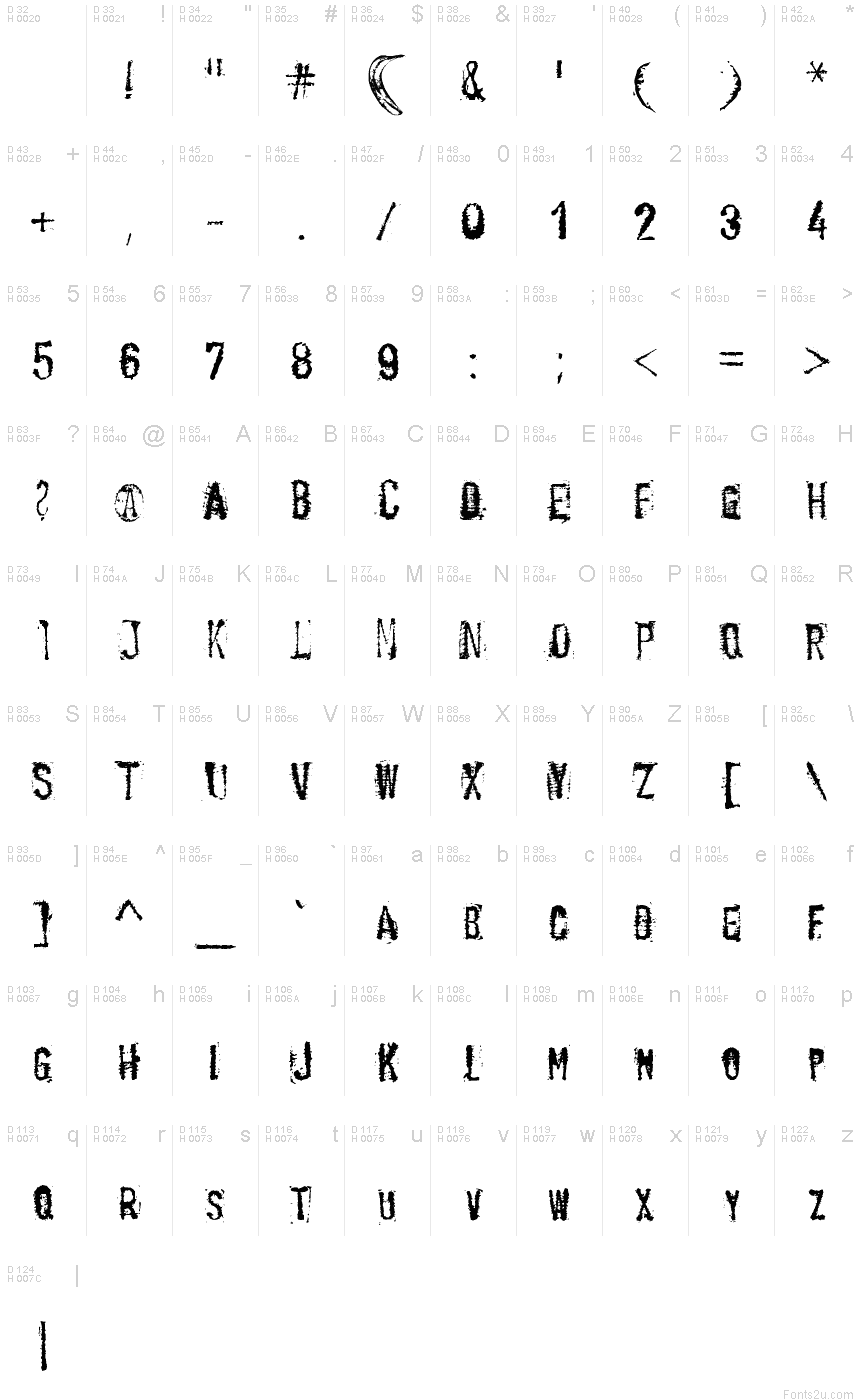
Banana Type je bezplatné display písmo s erodovanými velkými písmeny a surovou, seškrabanou texturou, díky níž vypadají písmena jako vyrytá přímo do stránky. Písmena jsou vysoká a nepravidelná, s roztřepenými okraji a popraskanými vnitřky, což celému designu dodává drsný, ručně poškozený vzhled namísto pouhého úhledného efektu zestárnutí.
Hodí se na hudební letáky, hororové plakáty, obálky zinů, titulní karty a streetwearovou grafiku, kde písmo musí působit syrově a bezprostředně. Jako bezplatný font také skvěle funguje pro krátké nadpisy, názvy kapel a monogramy, protože silná eroze propůjčuje i pár písmenům výrazný, otlučený vzhled.